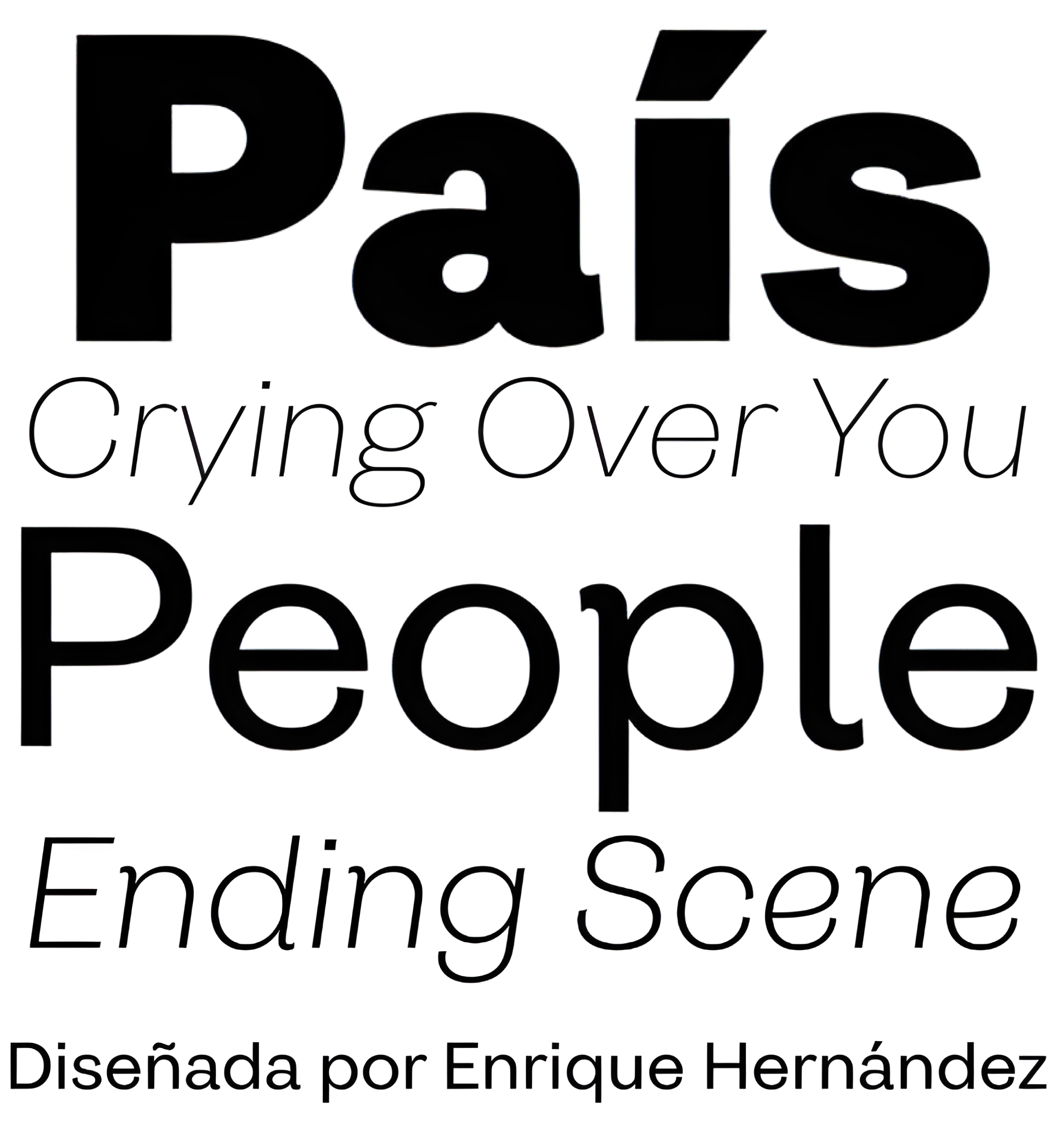
| Descripción | «País» es un grotesco sans serif contemporáneo y moderno, inspirado en los grotescos de principios del siglo XX, pero más geométrico y con una altura x más amplia que sus referentes; lo que lo hace ideal para los tiempos actuales. |